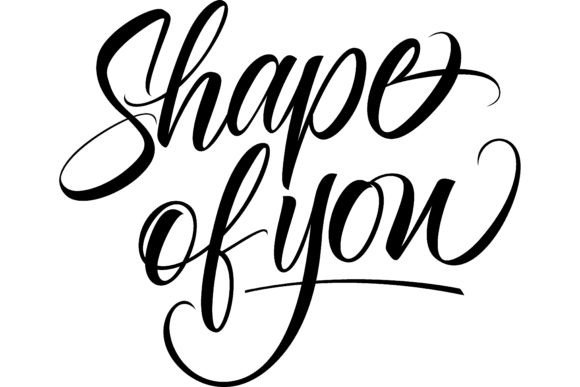
Shape of You Lettering. Calligraphic Ins
Ulasan Lengkap: Shape of You Lettering – Calligraphic Ins
Se você está em busca de uma tipografia que una elegância artesanal e emoção autêntica, o Shape of You Lettering da coleção Calligraphic Ins é a escolha certa. Cada traço foi cuidadosamente desenhado à mão, trazendo à tona aquela sensação única de um convite pessoal, perfeito para transformar cartões, pôsteres e mensagens privadas em verdadeiros destaques visuais.
- Design artesanal impecável – A caligrafia apresenta linhas fluidas e curvas suaves que lembram a escrita de um artista apaixonado, garantindo originalidade em cada peça.
- Versatilidade de uso – Ideal para greeting cards, convites, capas de álbum, posts de redes sociais e até mesmo para branding de pequenas marcas que desejam um toque humano.
- Emoção que conecta – As formas orgânicas do lettering despertam sentimentos de intimidade e calor, tornando a mensagem ainda mais impactante.
Em resumo, o Shape of You Lettering da linha Calligraphic Ins oferece não apenas um estilo visual deslumbrante, mas também a capacidade de transmitir sentimentos genuínos em cada caractere. Experimente e veja como suas criações ganharão vida, conquistando corações e cliques.